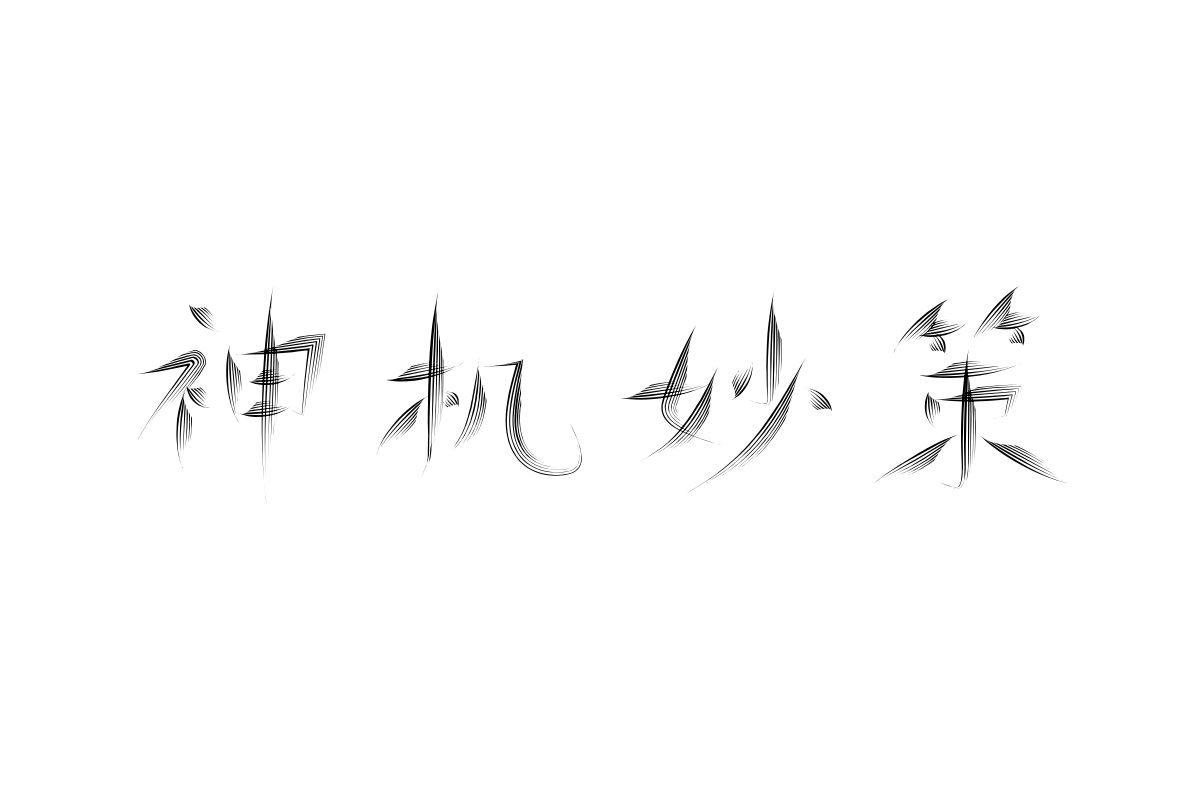
仓耳花语字体是一款具有独特风格的中文字体,它由仓耳设计工作室开发。这款字体以其独特的字形设计和丰富的字重选择而受到广泛欢迎。以下是对仓耳花语字体的一些介绍:
1. 字形设计:仓耳花语字体采用了传统的汉字结构,同时在笔画的处理上进行了创新。它的字形既有古典之美,又不失现代感,给人一种独特的视觉体验。
2. 字重选择:该字体提供了多种字重(字号大小)选择,以满足不同场合和需求的需求。无论是用于正式文件、广告宣传还是个人博客,都可以找到合适的字重。
3. 适用范围:仓耳花语字体适用于各种场景,包括网页设计、印刷品、海报等。它不仅适合商业用途,也适合个人使用,可以提升作品的美感和品质。
总之,仓耳花语字体是一款具有独特风格和丰富字重的中文字体,适合各种应用场景。无论你是设计师还是普通用户,都可以从这款字体中感受到中国传统文化的魅力。